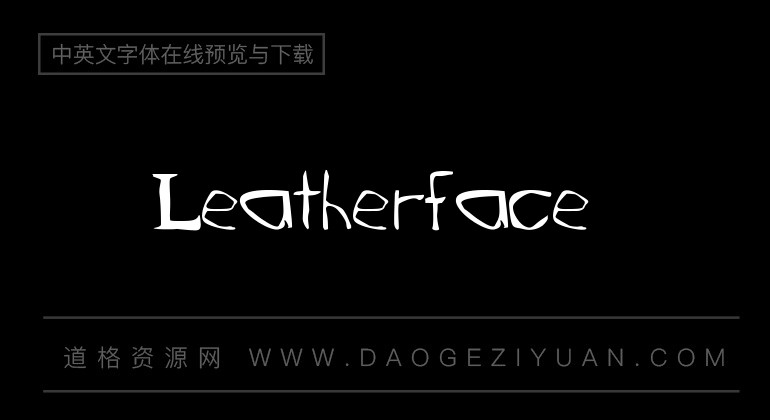
Leatherface 是一款受到传统手写字体的启发,由 Fontfabric 字体工作室创作的新字体。它具有独特的笔画,带有一种温暖的感觉,可以给任何设计创作带来活力和温暖的气息。它具有较强的表现力,可以用于各种类型的文字设计,从海报到广告,从书籍到杂志,从网站到品牌标识,都可以使用。它的字形设计更加灵动,给设计师更多的创作空间。内容介绍
Leatherface 是一款非常不错的手写艺术字体,具有很好的视觉感,适合于文化类的宣传设计、商业类品牌的广告和产品包装设计以及个性化文字排版等较多场景。